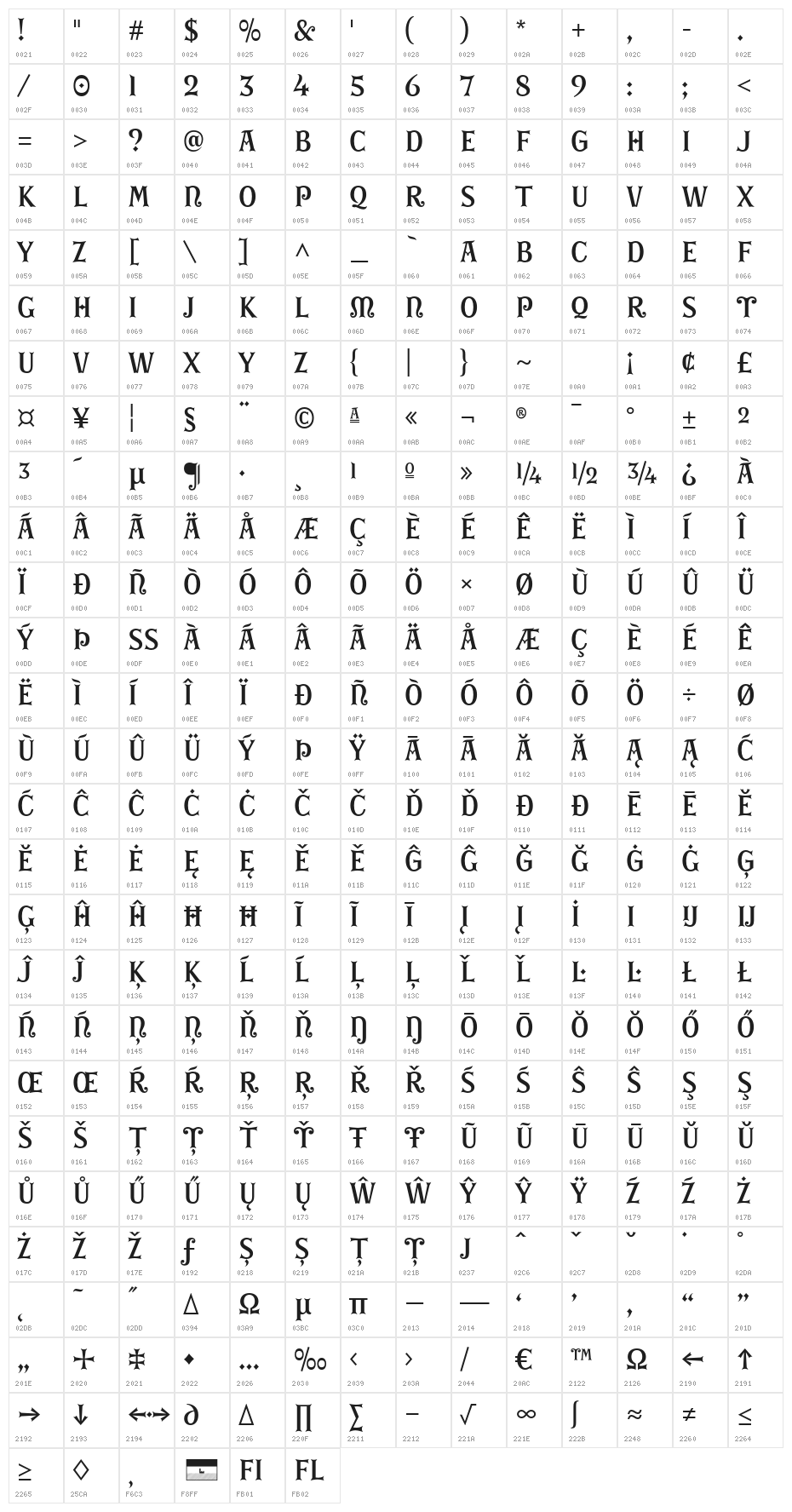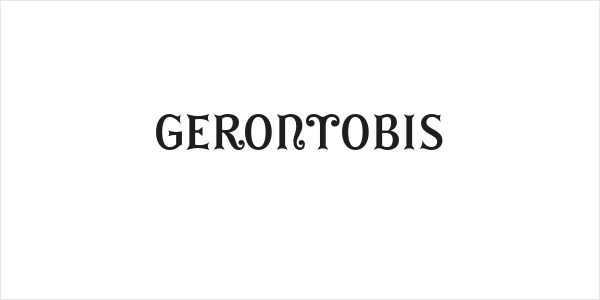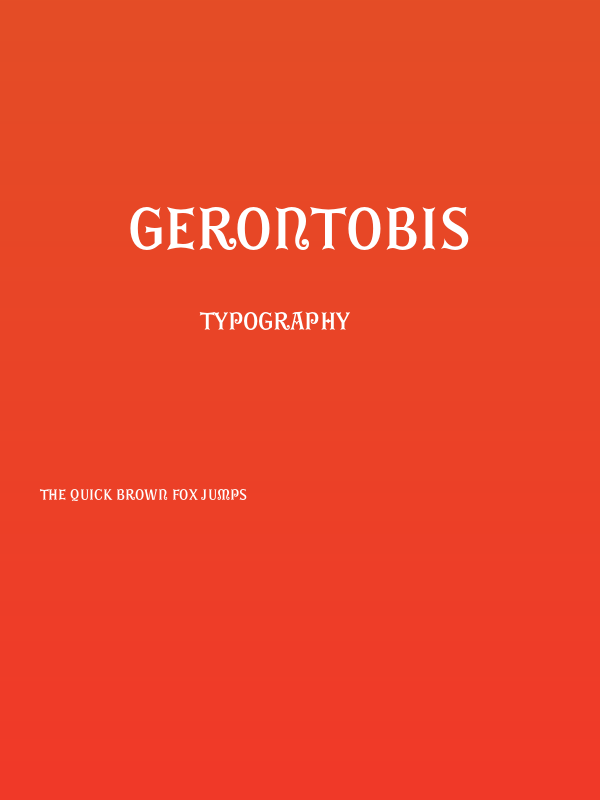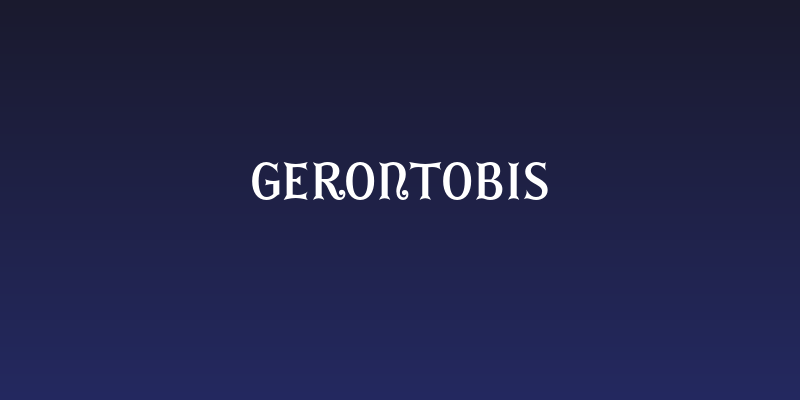
GErontoBis Font
✎ Gothic
| Categorie | Gothic |
| Caso d'uso | Headlines, Logos, Decorative text |
| Progetti proposti | Ideal for projects requiring a historical or gothic touch, such as book covers, posters, or branding for vintage-themed products. |